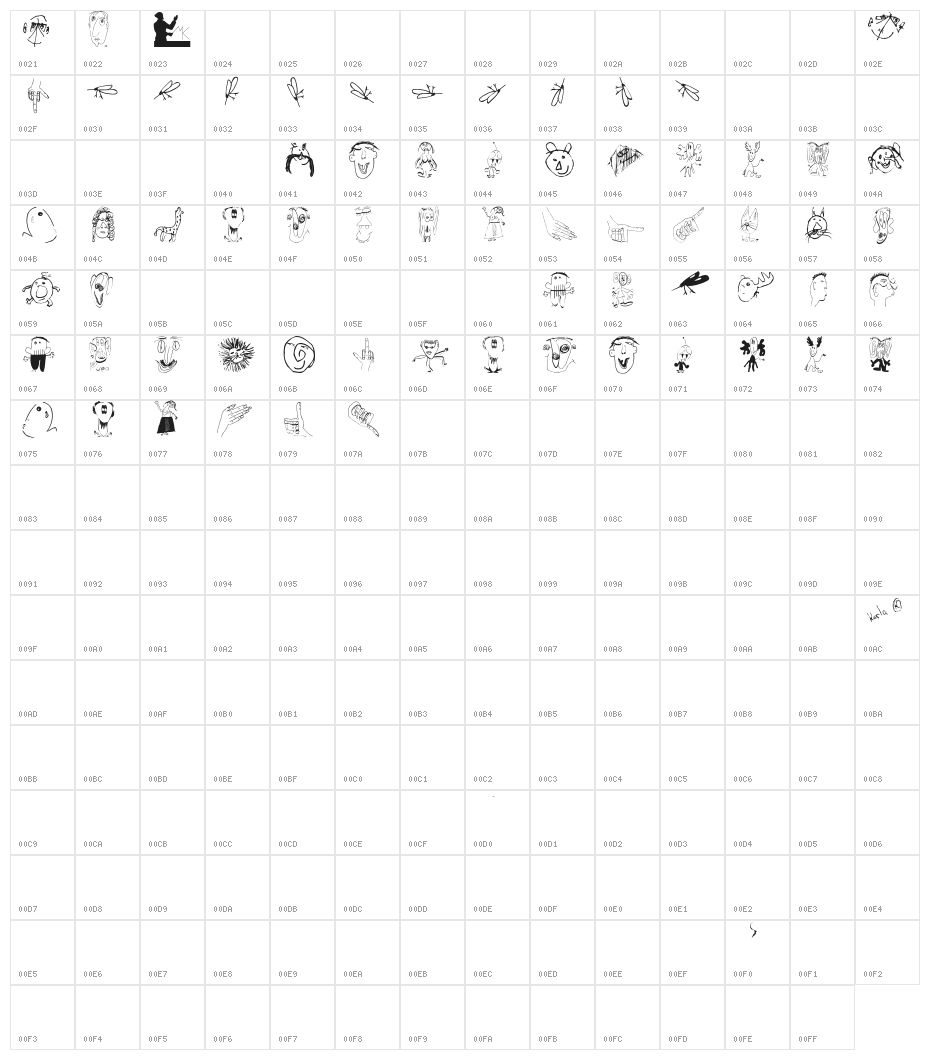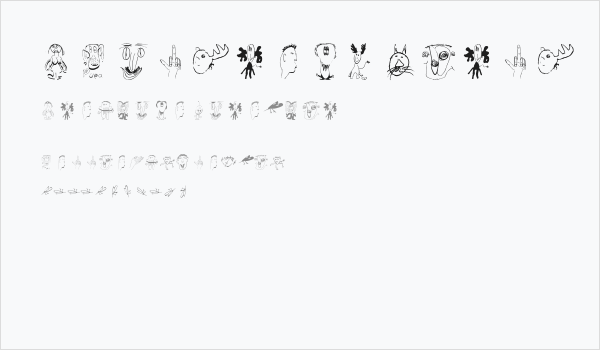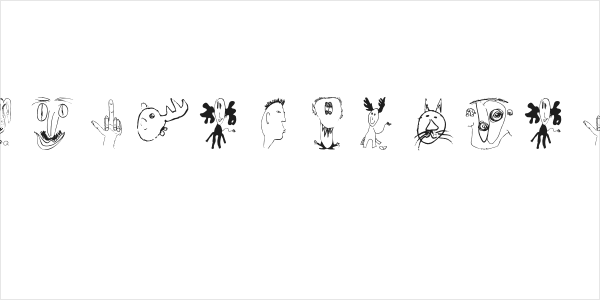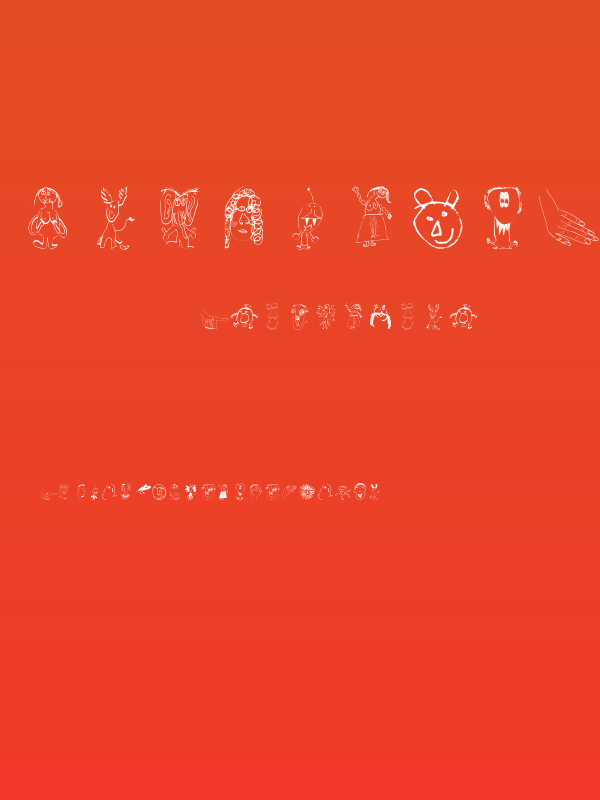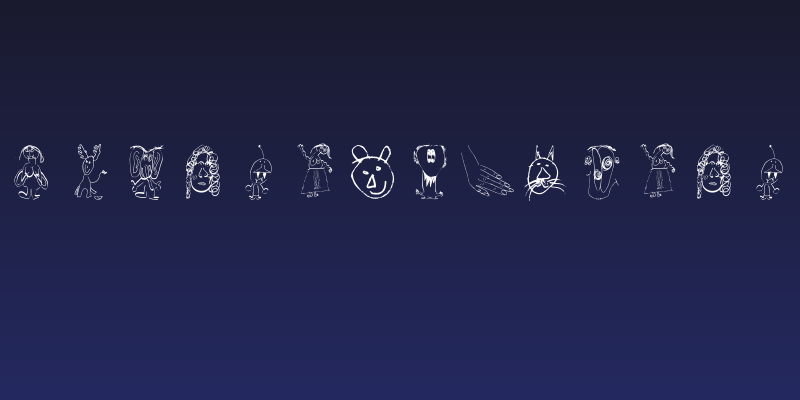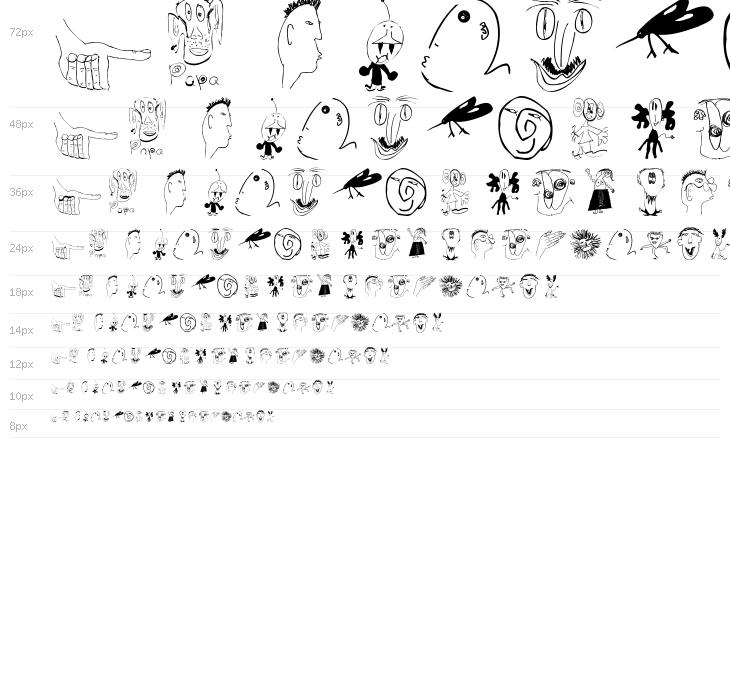
ChildrensWorld Font
| Stile generale | Playful, Whimsical, Artistic |
| Caso d'uso | Illustrations, Decorative elements, Creative projects |
| Progetti proposti | Ideal for children's book illustrations, playful branding, educational materials, or any project seeking a whimsical and creative touch. |